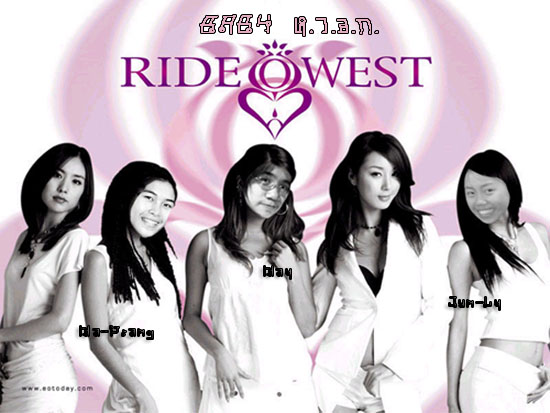
ช่วยดูภาพที่ตัดต่อหน่อยได้ไหมคะ
คือ...เพิ่งจะเคยทำอะไรแบบนี้เป็นครั้งแรก
ถ้าไม่ใช่เพราะอาจารย์สั่งเมย์ไม่ทำหรอก
คือว่าภาพนี้จะเอาไปทำสติกเกอร์น่ะค่ะ  :25:
ช่วยดูให้หน่อยได้มั้ยคะว่ามีตรงไหนบ้างที่ควรแก้
คือเมย์ก็เพิ่งตัดต่อรูปแบบนี้ครั้งแรกจริงๆน่ะค่ะ  :25:
จะบ้าตาย  อายเหมือนกันนะเนี่ย  แต่เพื่องาน  :05:
จริงๆ คือหน้ายังไม่สมดุลกับร่างกายค่ะ
เป็นจุดที่เด่นชัดที่สุดเลยนะ
รองลงมาก็คงจะเป็นการตัดต่อให้เนียน ยังไม่กิ๊งพอ  :42:
แล้วก็เรื่องฟอนต์ด้วย  :42:
ไม่เลยค่ะ
ดีซะอีกที่ติมา  เพราะจะทำให้เมย์ปรับปรุงแก้ไขดีขึ้น
อย่างที่บอกค่ะ  ว่างานนี้เป็นงงานที่ต้องตัดต่อรปในลักษณะนี้
เมย์ก็คิดแล้วล่ะว่าหน้าไม่สมดุลกับร่างกายโดยเฉพาะไอ้ปราง  :42:
ไม่เนียนจ้า
หน้า มุม มันไม่เข้าหน่ะ
ฟอนต์อ่านไม่ออกจะ  :21:
ผมว่าคนแรกจากซ้าย กับคนที่สี่ ก็เนียนดีนะครับ  :02:
ยังไม่ค่อยเนียน
แต่ผมว่าเอางี้แหละ ไม่ต้องเนียนมากหรอก ฮาๆ
คนขวาสุด มุมกล้องค่อนช้างดีแต่ผมมันตัดกันเข้มไปนิดนึงมันเลยดูหลอกตา ลองแก้นิดนะจ๊ะ
1. รู้สึกฟอนต์ไม่เหมาะ
2. รูปน้องเมย์ลองหามุมที่มันพอดีกันมาตัดต่อดู จะทำให้ตัดต่อง่ายขึ้น
3. ฝึกมือเรื่อยๆ แล้วจะดีเอง